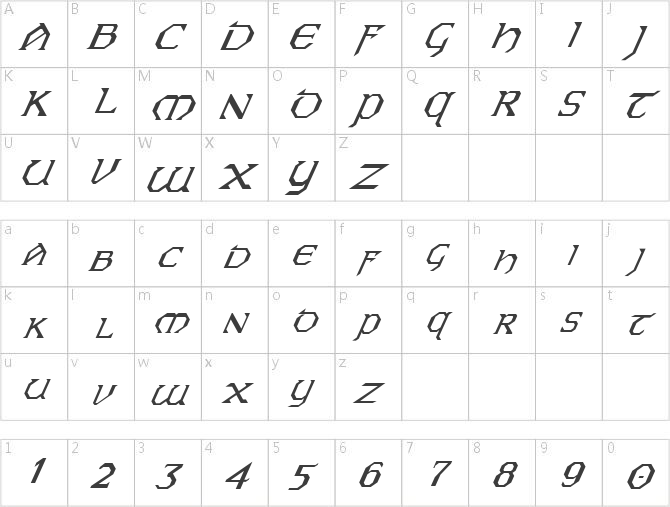
FZ JAZZY 31 ITALIC 詳情頁
字體名稱: FZ JAZZ
FZ JAZZY 31 ITALIC
FZ JAZZY 31 ITALIC介紹
FZ JAZZY 31 ITALIC字體字庫是一款讓人賞心悅目、百看不厭的英文字體,適合各類廣告和產品包裝設計應用,字體大小0.03MB,格式為ttf字體,上傳用戶是眾聯齊成,作者/版權方為未知